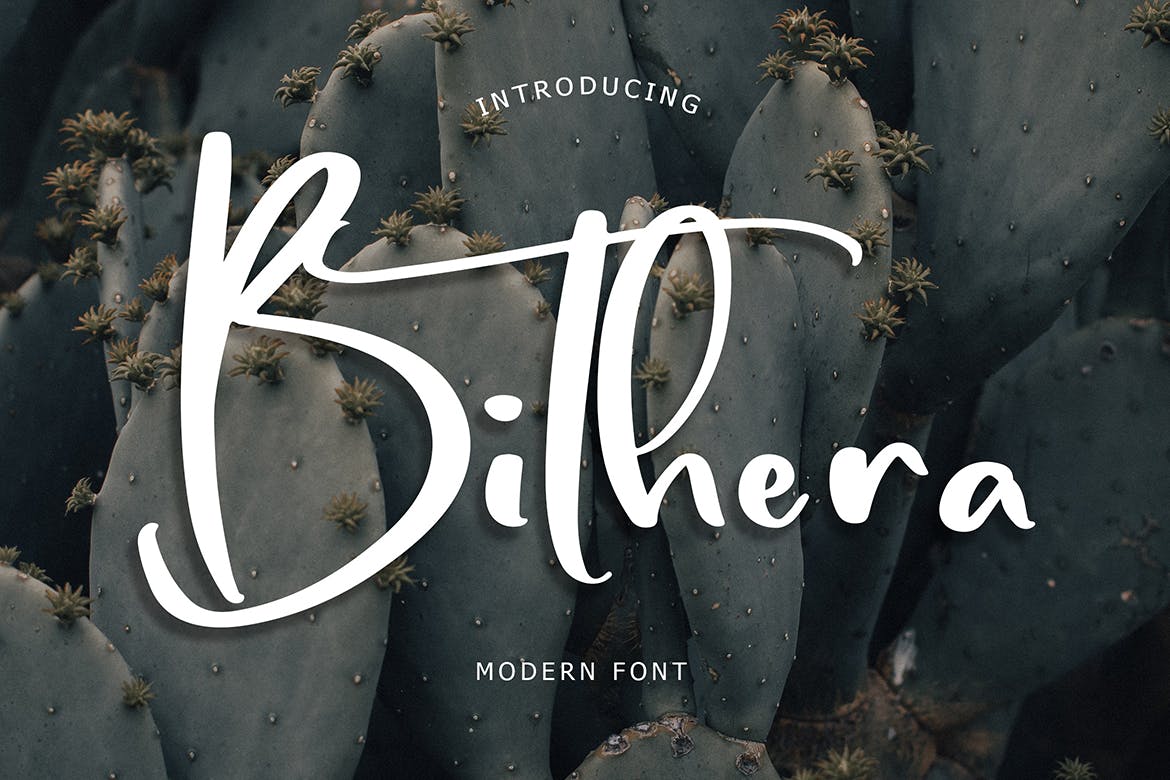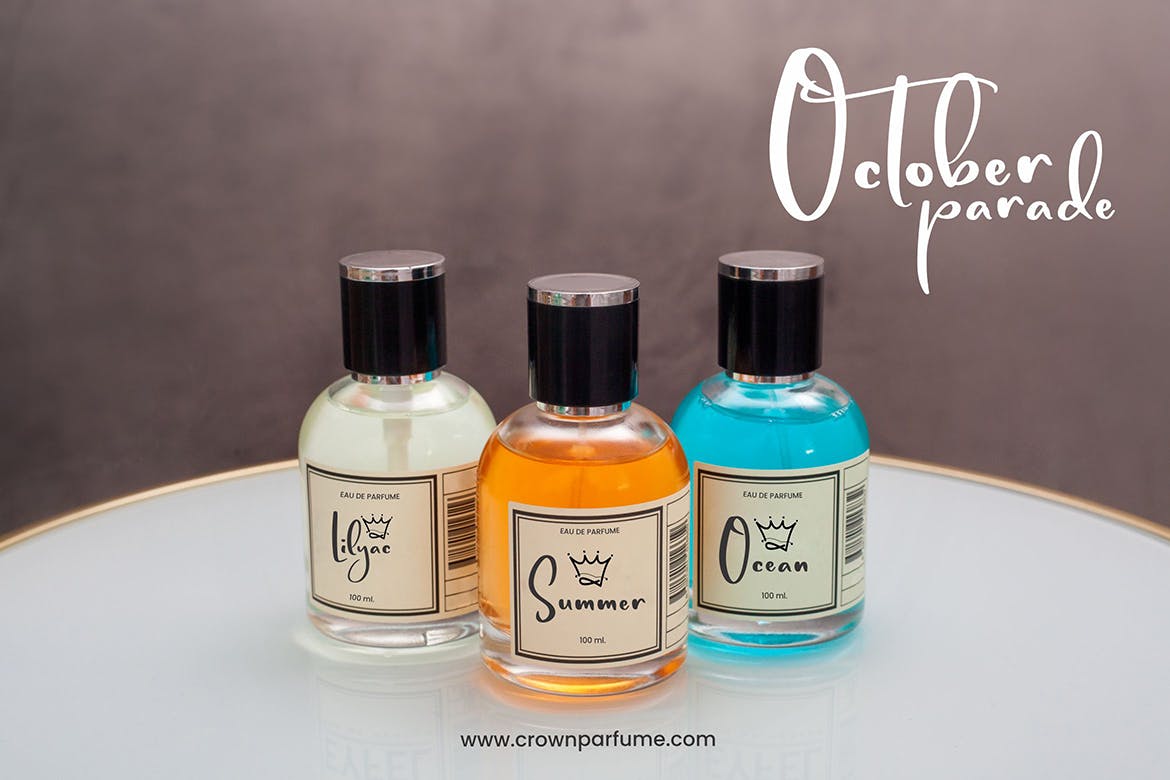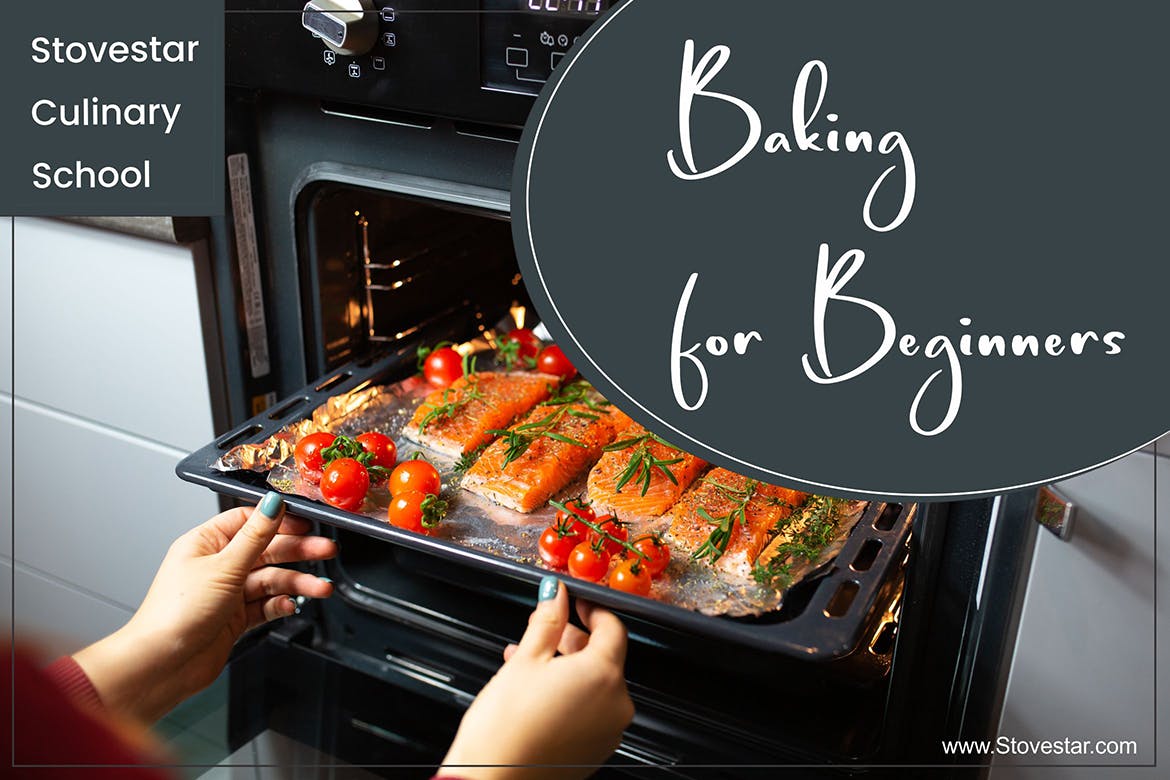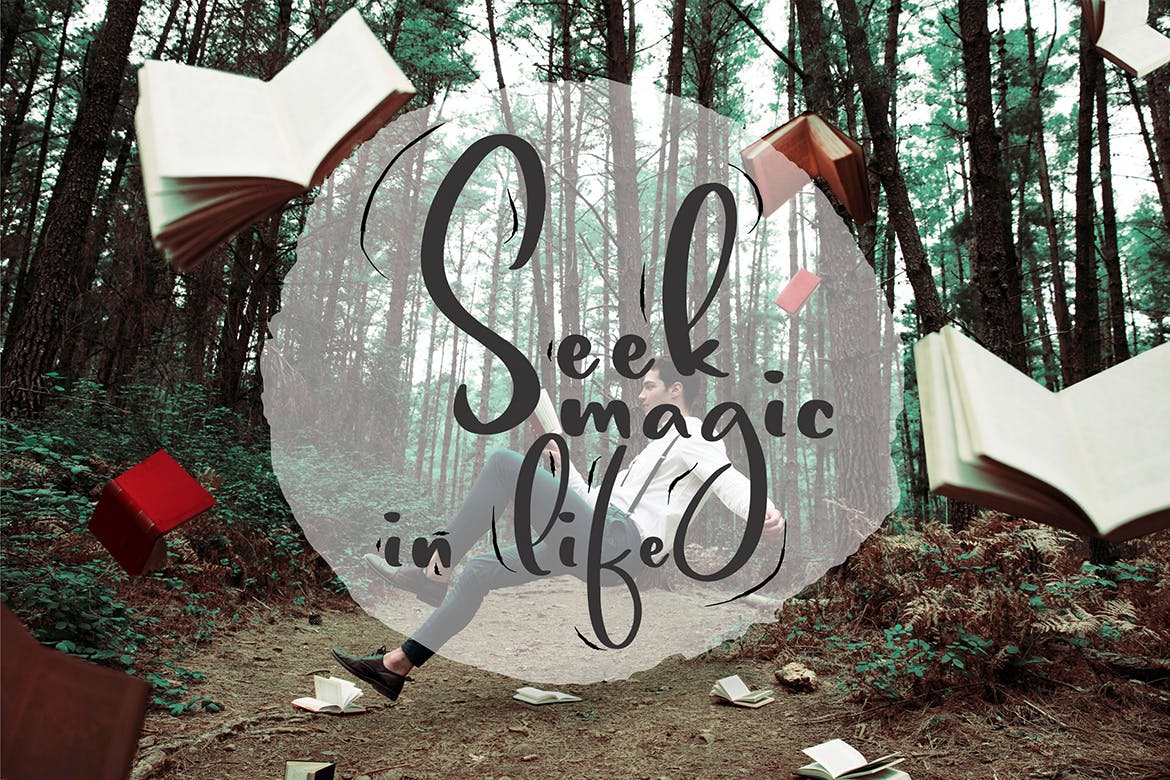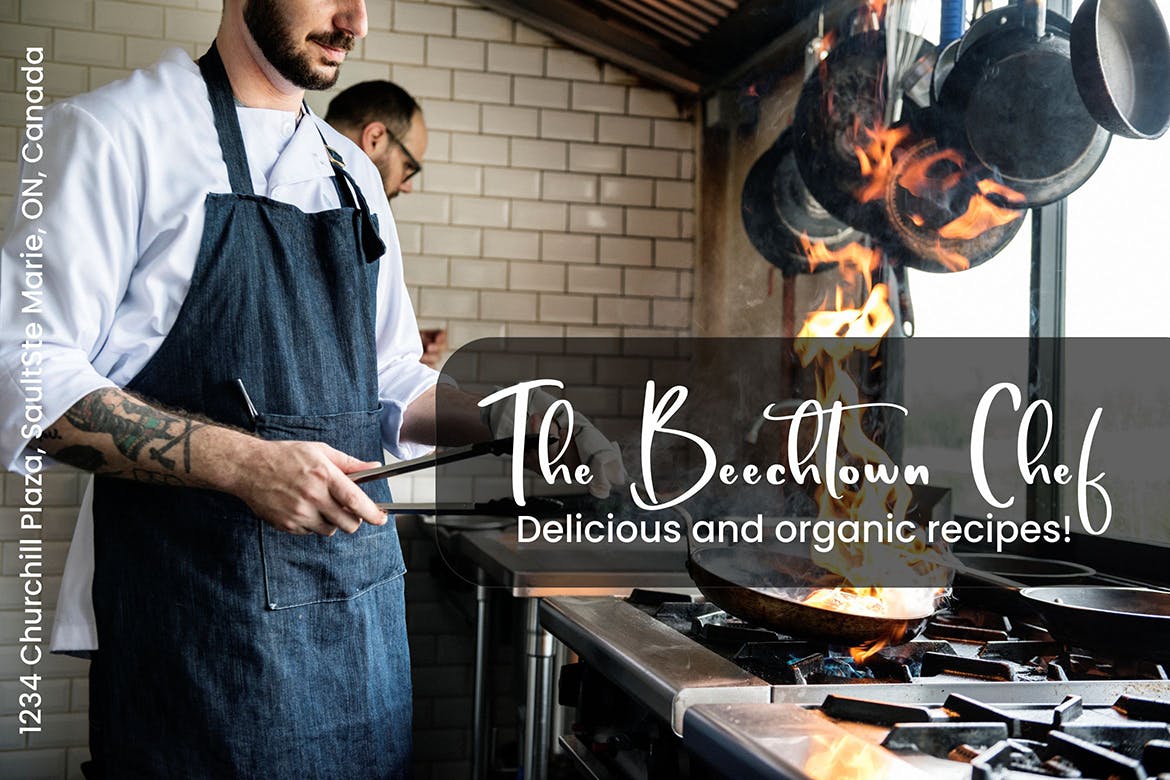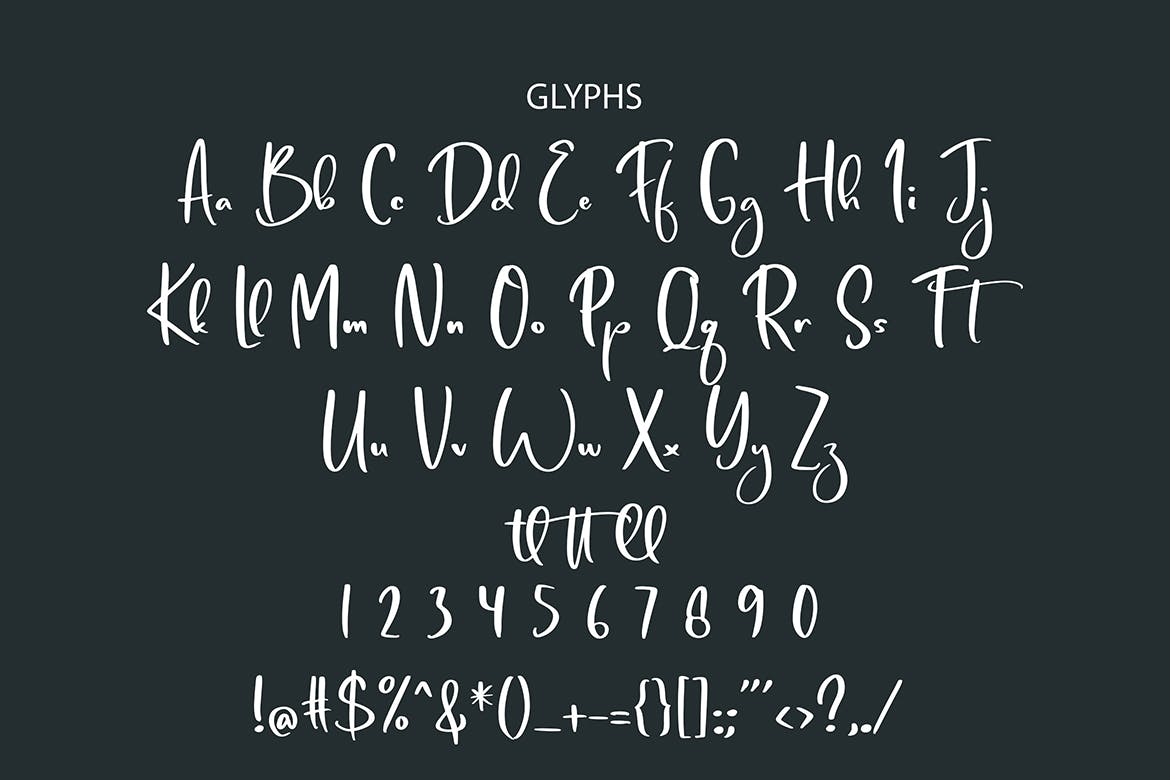
Bithera یک فونت مدرن دستنویس است که میتواند متن شما را زیبا، لوکس و مدرن جلوه دهد!
این فونت برای پروژههای برندینگ، لوگو، طراحیهای عروسی، پستهای شبکههای اجتماعی، تبلیغات، بستهبندی محصولات، طراحی تیشرت، طراحی محصولات، برچسب، عکاسی، واترمارک، دعوتنامه، لوازمالتحریر و هر پروژهای بسیار مناسب است.